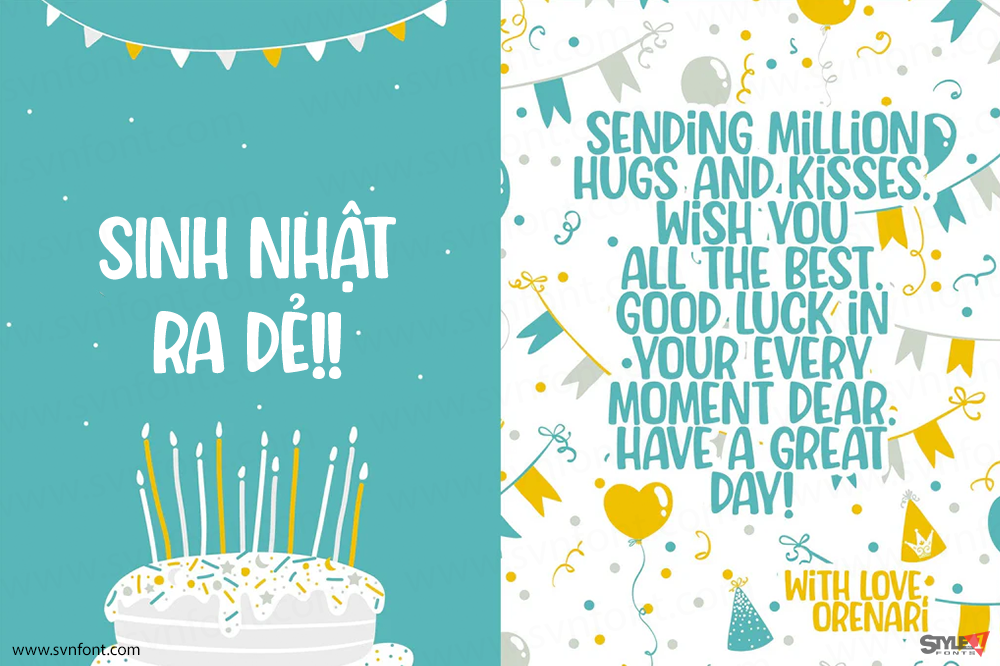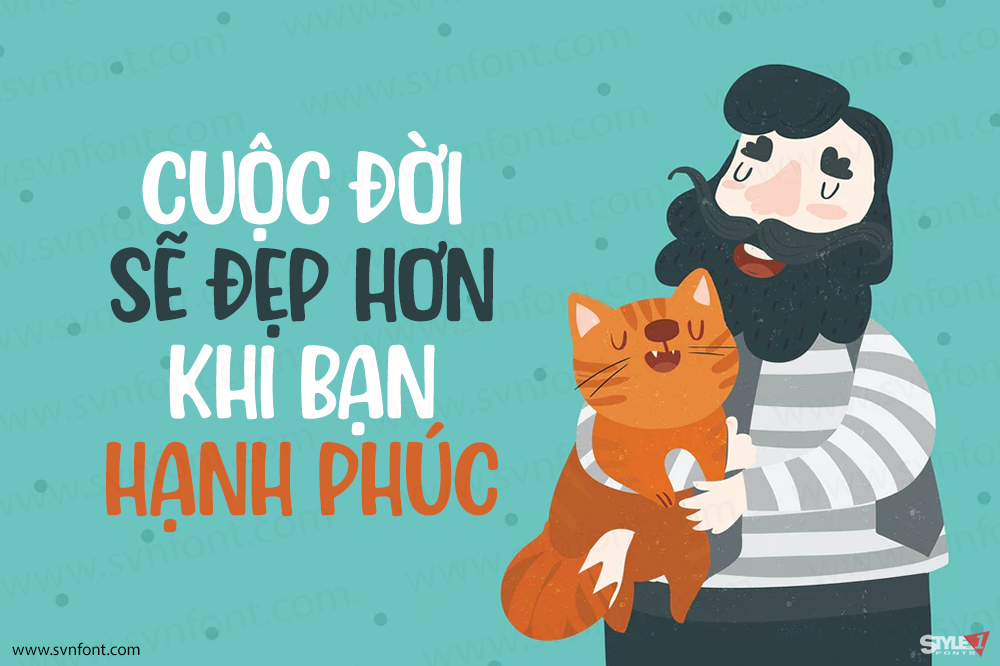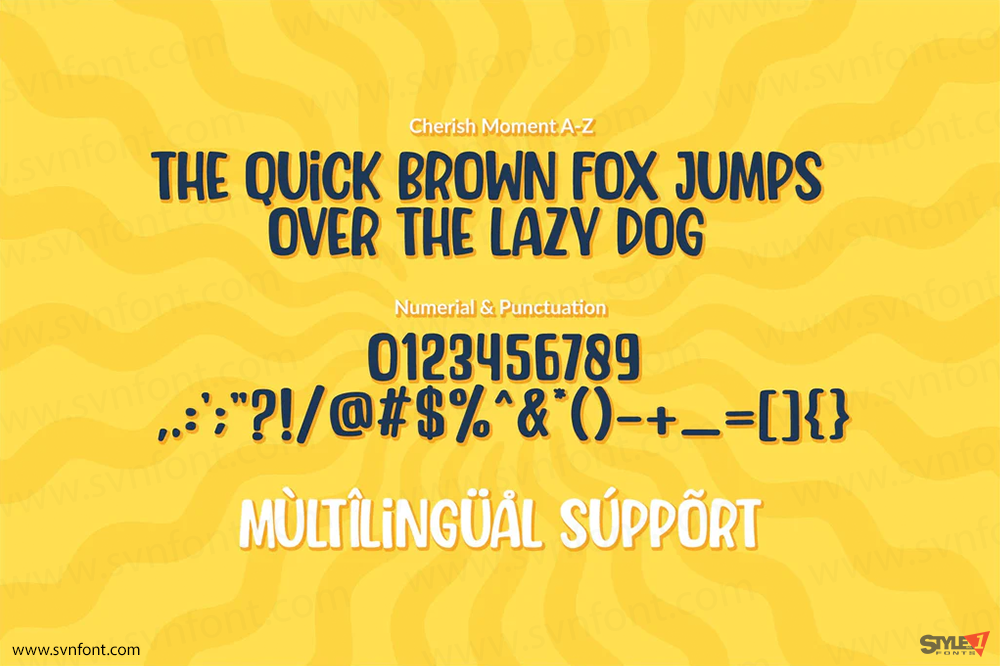
Cherish Moment là một font chữ đậm vui nhộn, mang đến cảm giác hạnh phúc và niềm vui. Phong cách tự nhiên, dễ thương của font giúp nó phù hợp với rất nhiều thiết kế và đồ thủ công, hoàn hảo cho mọi dịp. Hãy khuấy động thiết kế của bạn và tăng thêm sự thú vị với Cherish Moment.